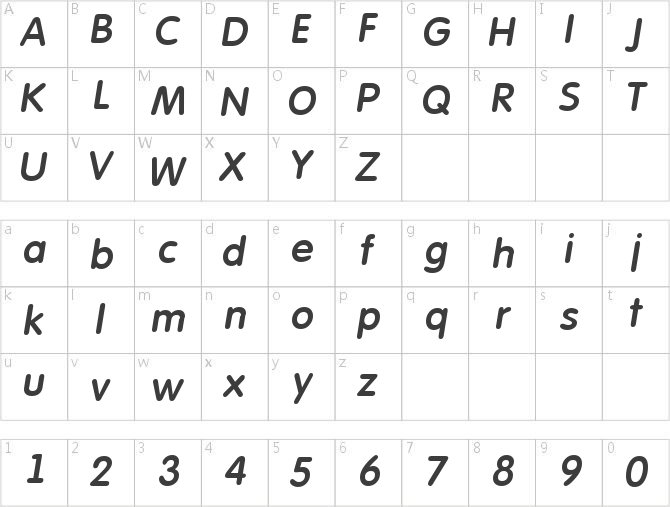
a_FuturaRoundDemi-Italic
a_FuturaRoundDemi-Italic介紹
a_FuturaRoundDemi-Italic字體字庫是一款讓人賞心悅目、百看不厭的英文字體,適合各類廣告和產品包裝設計應用,字體大小0.05MB,格式為ttf字體,上傳用戶是@小咖,作者/版權方為未知